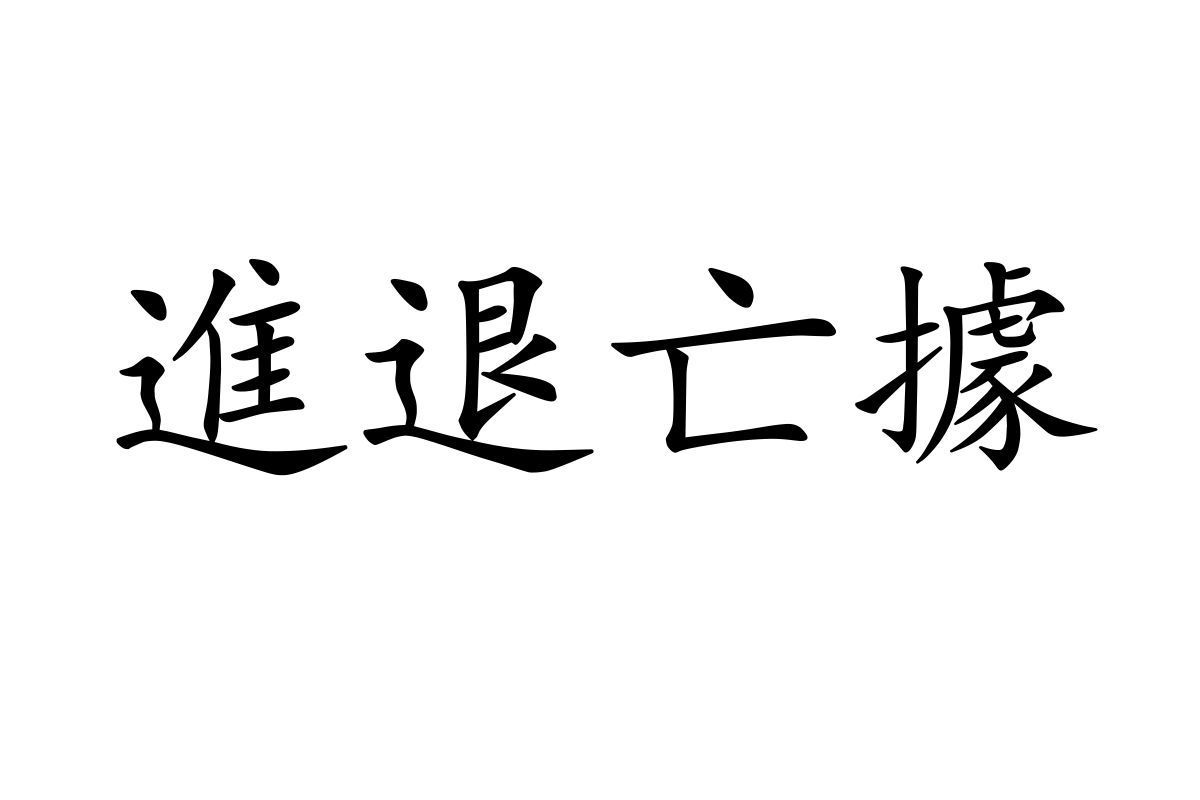
汉仪楷体繁是一套由汉仪公司开发的中文字体,主要用于排版和设计工作。这套字体的特点是字形规整、笔画清晰,适合用于各种印刷品和网络页面的排版设计。
汉仪楷体繁的特点如下:
1. 字形规整:汉仪楷体繁的字形结构紧凑,笔画分明,易于阅读和识别。
2. 笔画清晰:每个笔画都经过精心设计,线条流畅,没有多余的装饰,使得整体视觉效果更加简洁大方。
3. 适用范围广泛:这套字体适用于各种印刷品和网络页面的排版设计,无论是书籍、报纸、杂志还是网页、广告等,都能展现出良好的视觉效果。
总之,汉仪楷体繁是一款功能强大、适用范围广泛的中文字体,适用于各种排版设计工作,能够满足用户在不同场景下的需求。